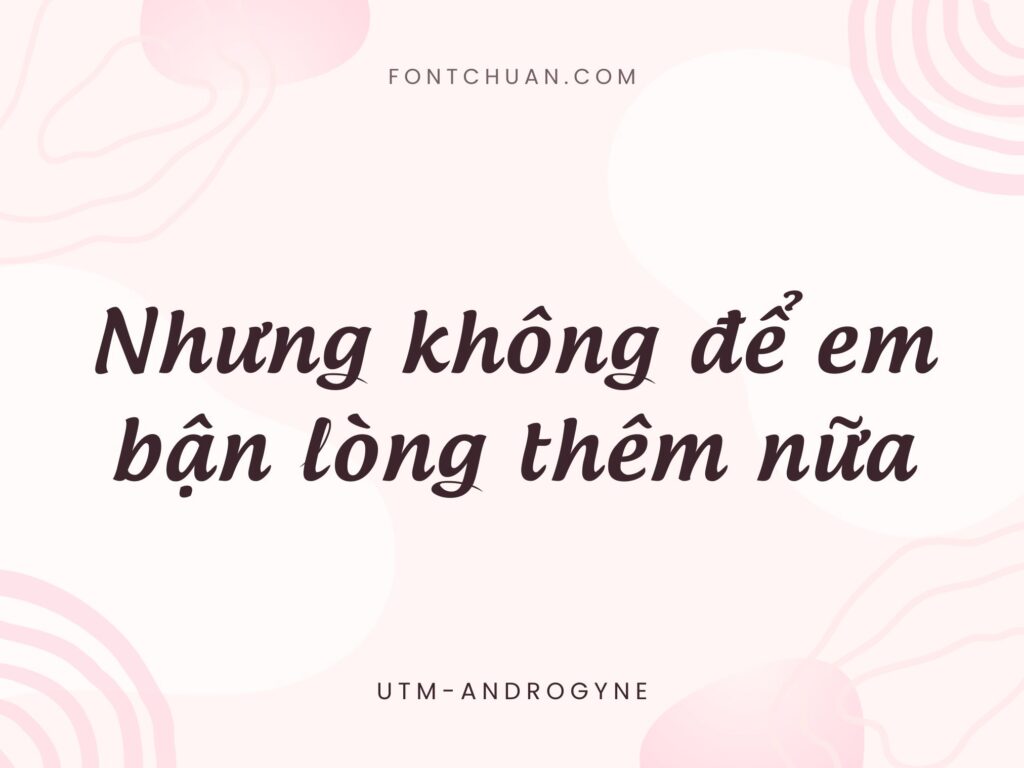
Font UTM Androgyne Việt Hóa
UTM Androgyne là một Font Script mang phong cách hiện đại, được thiết kế bởi Dimitri Castrique với sự kết hợp giữa đường nét mềm mại và cá tính mạnh mẽ. Font sở hữu nét độc đáo trong hình dáng chữ, thể hiện được sự sáng tạo và khác biệt trong thiết kế. Phiên bản Việt hóa do Đinh Kiên thực hiện, hỗ trợ đầy đủ tiếng Việt và hơn 100 ngôn ngữ khác. Đây là một trong những font được thành viên Font Chuẩn sưu tầm và chọn lọc để phục vụ các dự án đòi hỏi tính nghệ thuật và cá nhân hóa cao.
UTM Androgyne có cấu trúc chữ viết tay cách điệu, độ tương phản cao giữa nét thanh và nét đậm, cùng các đường lượn cong giàu biểu cảm. Font phù hợp để sử dụng trong thiết kế tiêu đề, poster, thiệp mời, bao bì và các ấn phẩm truyền thông cá nhân. Những ngành nghề như quảng cáo, thiệp cưới, giáo dục và công nghệ hoàn toàn có thể ứng dụng UTM Androgyne để tạo dấu ấn riêng biệt và thu hút trong thiết kế.